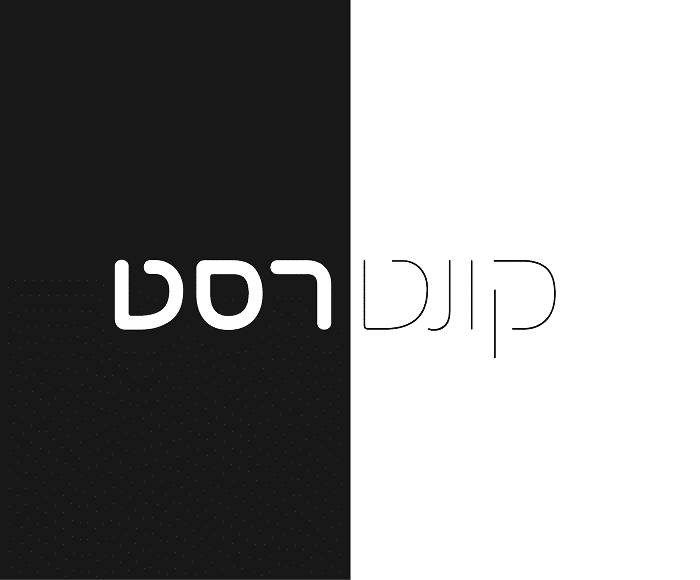
ניגודיות היא לא רק עניין של צבעים. בעולם העיצוב הגרפי, ובעיקר בעיצוב טקסט, היכולת להבליט, להכווין, ולתת דגש – נשענת על תצורת טקסט חכמה. הפונטים שאנחנו בוחרים קובעים את הטון, הדינמיקה והמסר הרבה יותר ממה שנדמה.
כאשר מדובר בעברית, המשימה הופכת קצת יותר מורכבת: השפה הכתובה מגוונת, עם מבנים צורניים שונים לגמרי מהלטינית. כדי להשיג ניגודיות ופוקוס בעזרת פונטים, צריך לדעת לבחור נכון – לא רק מה יפה, אלא מה עובד.
ניגוד טיפוגרפי יכול לנבוע מהמון דברים: עובי הקו (weight), גובה האותיות (height), רוחב הגופן (width), ריווח בין אותיות, צבע, ואפילו מרקם.
במילים אחרות – גם אם כל הטקסט באותו צבע, אפשר ליצור ניגוד חד באמצעות שימוש בפונט עבה לכותרת ובפונט דק לפסקאות. אפשר לשלב כתב מסורתי עם כתב מודרני, או כתב זוויתי מול כתב עגול.
המטרה ברורה: שהקורא יבין מה חשוב יותר, על מה לשים עין קודם – לפני שיקרא שורה אחת. ניגוד נכון הוא כזה שלא צריך להסביר אותו, הוא פשוט קורה.
אחד הכלים הכי חשובים בניגודיות הוא היררכיה טיפוגרפיה. היררכיה נכונה אומרת: הנה מה שצריך לקרוא קודם, והנה מה שמגיע אחר כך.
איך יוצרים את זה? קל: הגדילו את הפונט של הכותרת, הפחיתו את עובי הטקסט המלווה, שנו צבעים, או בחרו שני פונטים שונים שמדברים באותה שפה ויוצרים דינמיקה. זה כמו דיאלוג בין שתי דמויות שונות: כל אחת עם הקול שלה. וכשהן מדברות נכון – הקורא פשוט מקשיב עד הסוף.
הרבה מעצבים שואלים את עצמם – איך משלבים שני פונטים בלי שייראה חובבני? התשובה: התאימו תכונה אחת ושברו אחרת. למשל: שני פונטים עם גובה דומה, אבל אחד עבה והשני דק. או פונטים באותו סגנון (למשל: שניהם סנס־סריפיים), אך שונים ברוחב או במבנה האות.
הכלל פשוט: ליצור מתח – בלי לייצר ריב. כשהשילוב נכון, העין נמשכת למקומות הנכונים, והטקסט כולו נשמע כמו יצירה הרמונית.
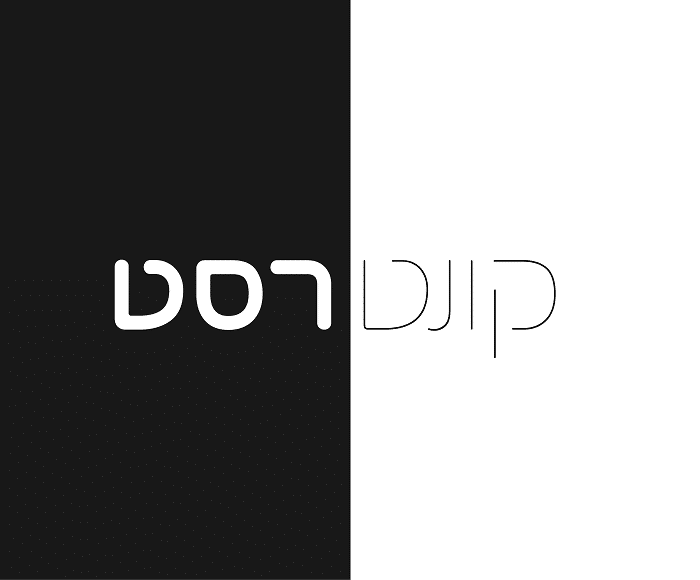
מעבר לכל הכללים, חשוב לזכור שצורת הכתב היא שפה בפני עצמה. גם אם לא לומדים אותה באקדמיה, כולם "מרגישים" כשזה טוב. פונט אחד יכול לשדר חגיגיות, אחר יכול לשדר דרמה, ושלישי מרגיש כמו הזמנה למסיבת גינה. הוא מעביר תחושה בלי לתרגם.
כדי ליצור טיפוגרפיה שעובדת – צריך לא רק להבין עיצוב, אלא להבין אנשים. מה יעצור את הקורא? מה יגרום לו להרגיש משהו? זו לא שאלה של צבעים בלבד – אלא של בחירות טקסטואליות חכמות.
אחת הדרכים ליצור ניגוד מיידי היא לשלב פונט טכני עם פונטים כתב יד בעברית. השילוב הזה יוצר קונטרסט בין "רשמי" ל"אישי", בין "מודפס" ל"נכתב במיוחד בשבילך". בעזרת פונט כתב יד אחד בלבד, אפשר לשבור את המבנה הגרפי – ולתת לטקסט מראה חי, נושם ובלתי צפוי. וזה בדיוק מה שגורם לו לבלוט.
שילוב של פונט SVG בעיצוב מאפשר עומק, מרקם וטקסטורה ברמות שלא הכרנו קודם. מדובר בפונטים שמבוססים על גרפיקה וקטורית ולא רק קווים פשוטים – מה שמוסיף רובד עיצובי נוסף. כשמשלבים בינו לפונט רגיל, מתקבל קונטרסט בין מרקם חלק למרקם עשיר – וזה אחד הכלים הוויזואליים הכי חזקים בעיצוב עכשווי.
לסיכום, ניגודיות טובה לא נוצרת במקרה. היא תוצאה של בחירות מדויקות, של הבנה טיפוגרפית ושל רגישות למסרים. כשמשתמשים נכון בפונטים עבריים – גם בלי תמונה אחת, אפשר ליצור עיצוב שמעביר רגש, סדר ומשמעות.
ניגודיות יוצרת סדר ומכוונת את העין. בלאגן נובע משילובים לא מדויקים ולא מקצועיים ללא היררכיה ברורה.
אפשר – אך רק אם כל אחד מהם משרת תפקיד ברור, ויש קו מנחה שמחבר ביניהם.
שילוב בין משקלים שונים של אותו פונט, או הכנסת פונט טקסטורלי כמו SVG לצד פונט רגיל.